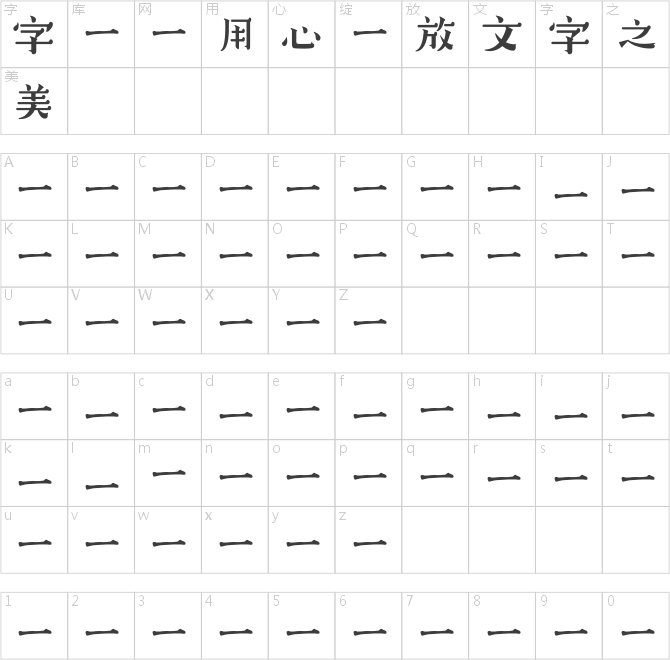
方正高原明朝体 详情页
字体名称: 方正高原明朝体
方正高原明朝体
方正高原明朝体是一款以作者母亲名字命名的字体,字形基于宋体经典且优雅的结构设计而成,减少了宋体具有相对锋芒修饰感的字脚,笔画圆润工整,韵律节奏恰如其分,构建出一款字形修?、匀称、雅韵,极具干练?华之气质美感的家族字体。 此款字体适合时尚、医美、化妆品类行业广告用字及画报杂志标题。